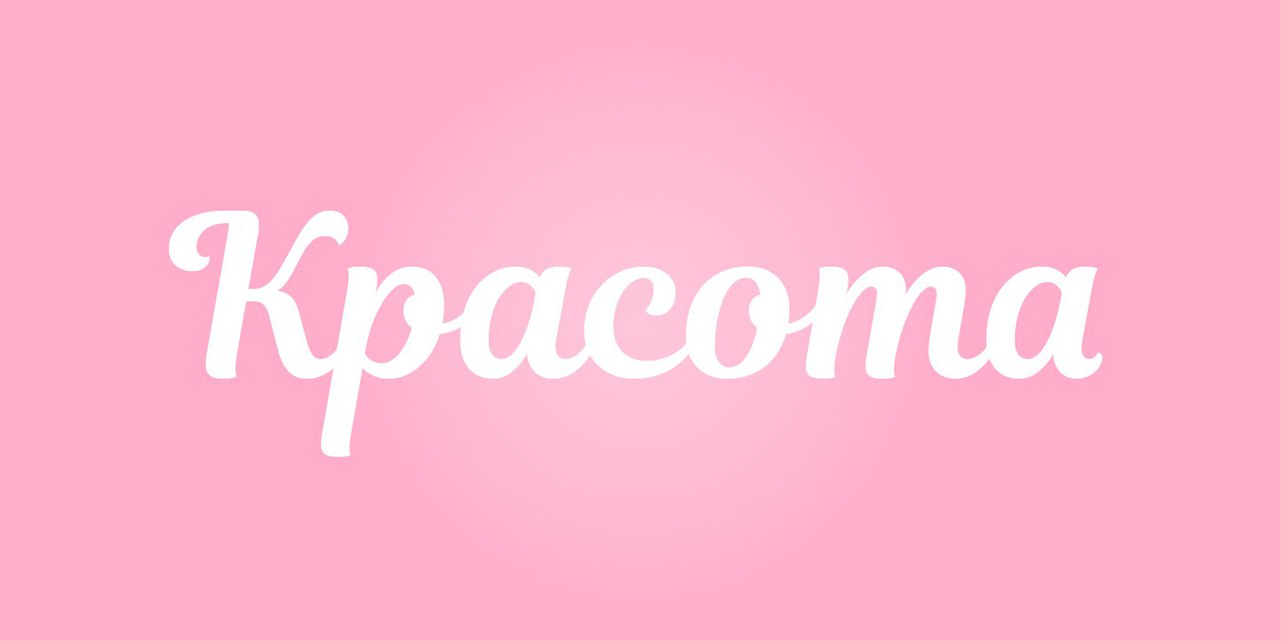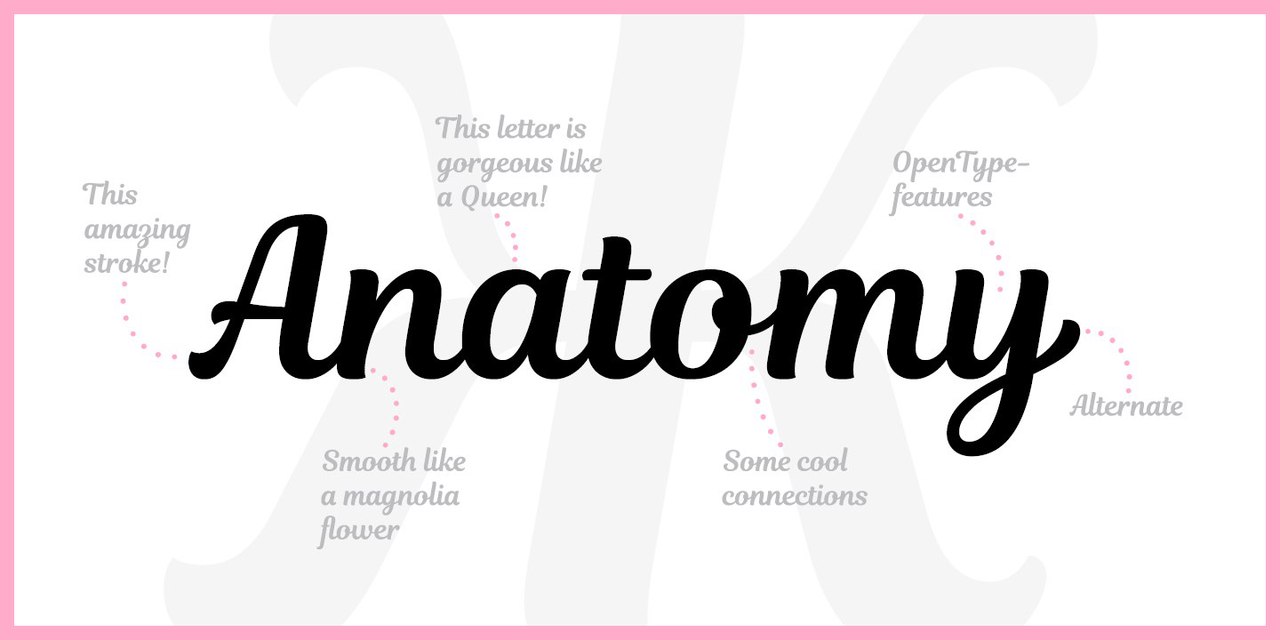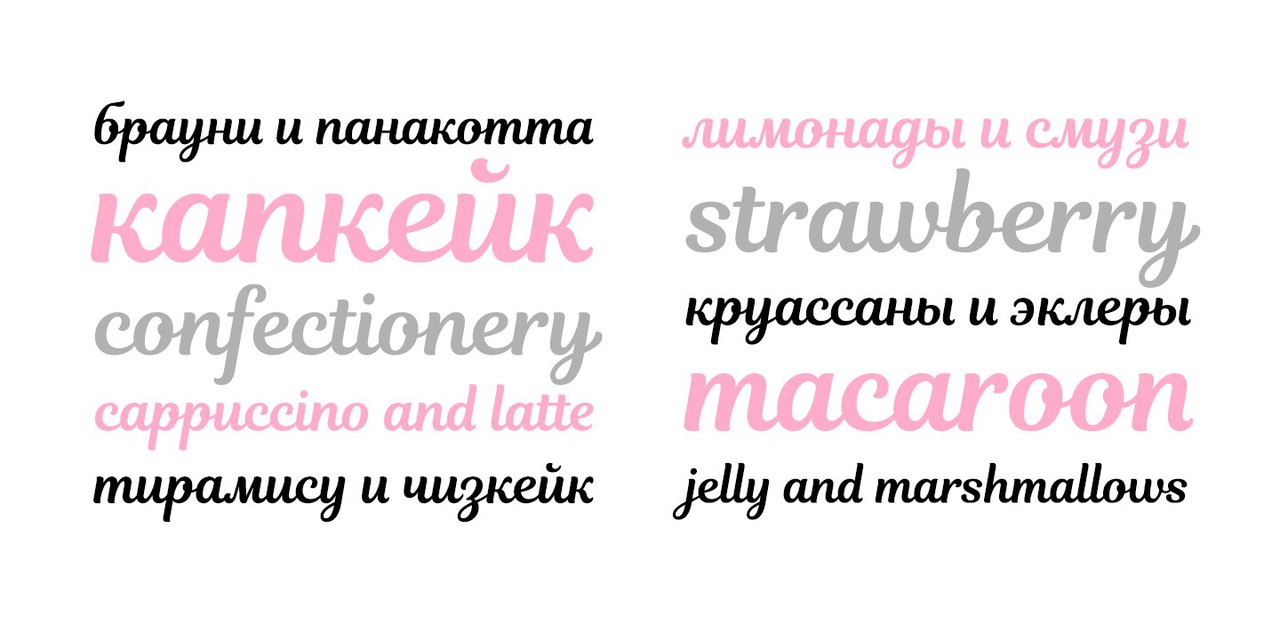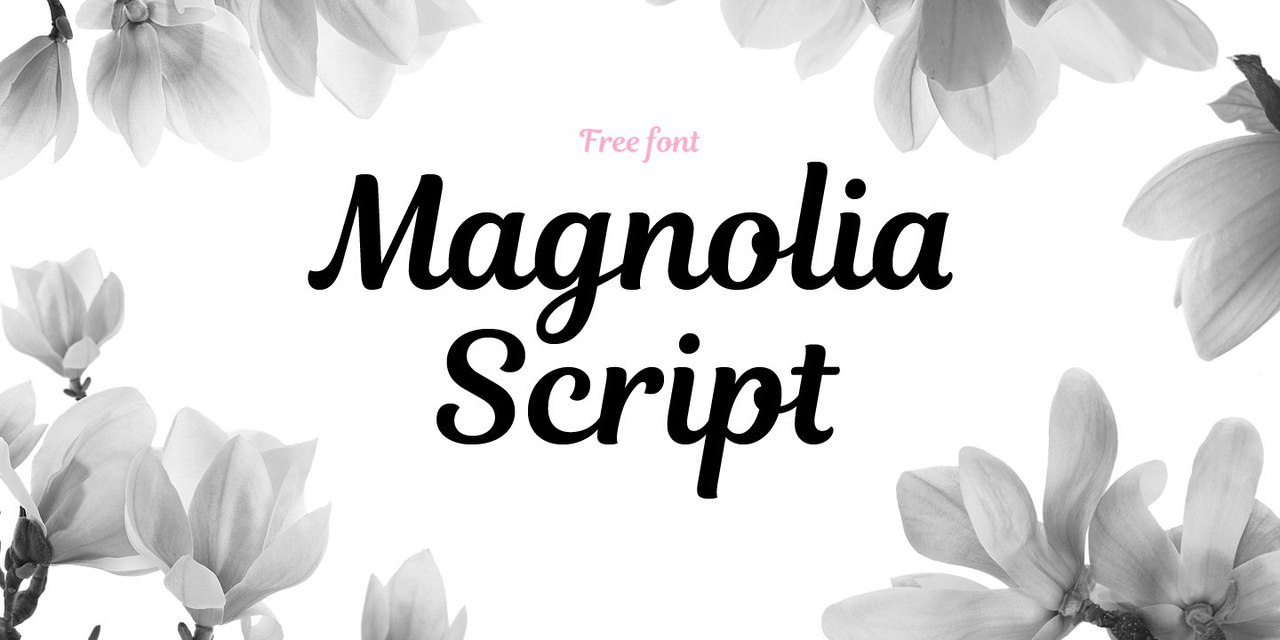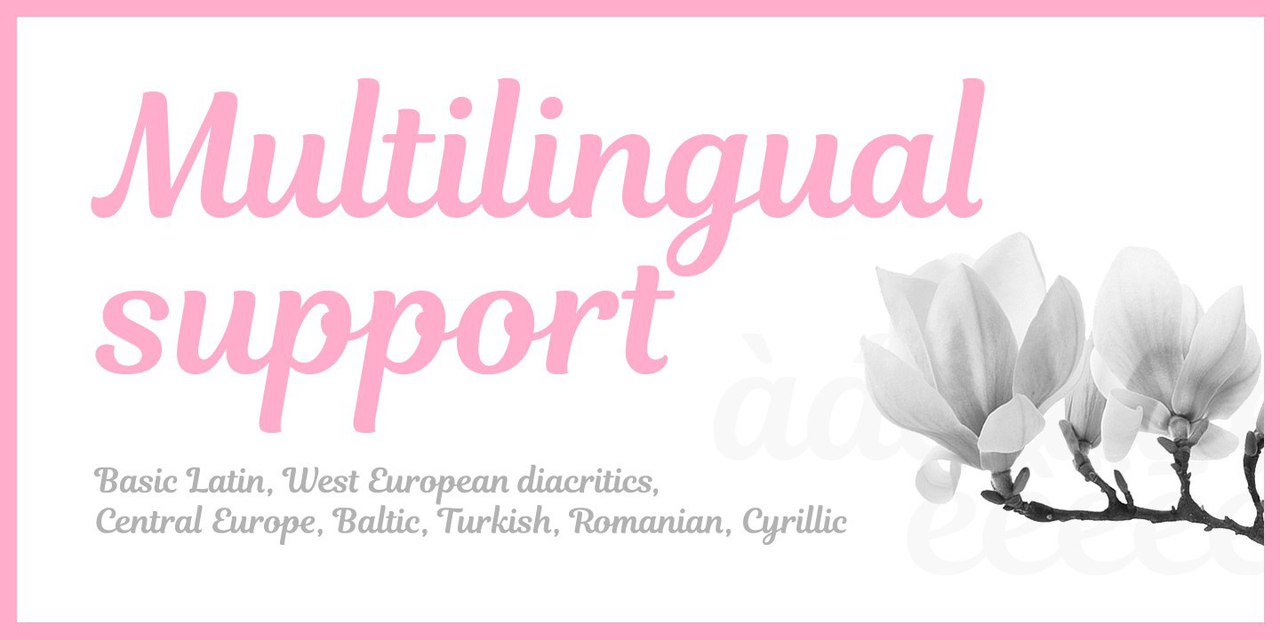
БЕСПЛАТНЫй ШРИФТ MAGNOLIA SCRIPT
Дизайнер шрифта Таня Черкиз начала делать этот шрифт в июне 2015, за это время было сделано две версии. Первая в релиз не пошла, а была полностью переработана как с визуальной стороны, так и с технической. В качестве релиза мы предлагаем аудитории восьмую сборку второй версии.
Под опентайп часть был разработан технический регламент, который описывал все взаимодействия букв между собой, в итоге весь шрифт — это большая опентайп фича с контекстными альтернативами (не забудьте включить поддержку ОТ, если у вас эта кнопка не нажата). За чудесный код мы благодарны нашему другу Денису Серикову, который с доблестью преодолел трехкратное переписывание кода из-за вновь появляемых обстоятельств.
Для каждого текстового знака в шрифте есть как минимум одна контекстная альтернатива, у некоторых знаков таких альтернатив до 5 штук на знак. Альтернативы работают самостоятельно, без вашего участия. В процессе работы со шрифтом начинаешь понимать, что буквы неожиданно меняются на альтернативы в процессе набора текста. Кто мастерски копнёт поглубже, увидит еще один стилистический сет, который запрятан на всякий пожарный случай.
Magnolia Script — это очень нежный и добрый цветочный шрифт, который производит впечатление своей естественной красотой. Шрифт Магнолия — это определенно девушка, можно даже сказать шрифтесса, которая расцвела и готова подарить свою красоту окружающему миру.
Автор шрифта: Таня Черкиз